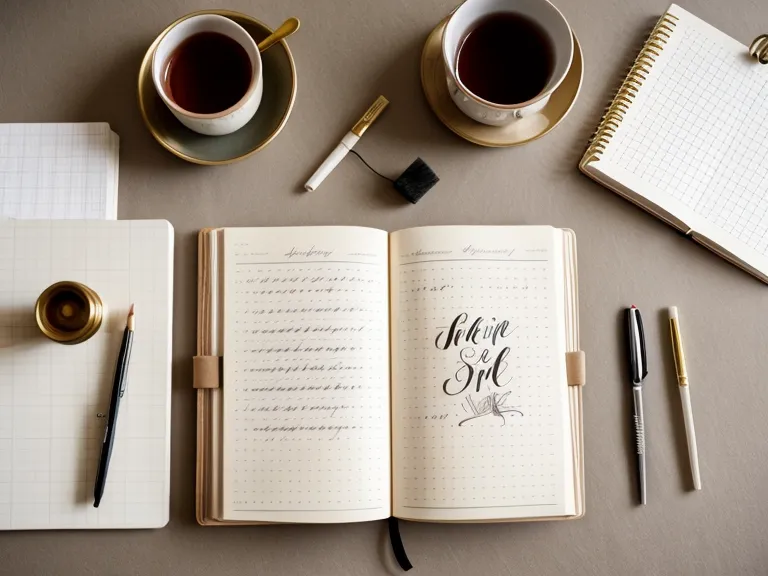
Achtzehn Übungsbögen liegen in der Mappe, mit der ich meinen Lernfortschritt tracke, jede Seite oben mit dem Namen des Kurses beschriftet, aus dem sie stammt. Diese Sammlung beantwortet die Frage nach der Handlettering lernen Dauer ehrlicher als jeder Vorher-Nachher-Post im Netz: Wer wissen will, wie lange es bis zu einem sauberen Schriftbild dauert, sollte weniger auf Kalenderwochen schauen und mehr auf die reine Anzahl der Übungseinheiten. Bei drei bis fünf Einheiten pro Woche zeigt sich ein spürbar saubereres Schriftbild nach sechs bis zwölf Wochen – wechselt man dabei die Technik, etwa von Monoline zu Brush, beginnt diese Uhr wieder bei null. Genau diesen Unterschied zwischen einem strukturierten Handlettering-Kurs und freiem Üben ohne Plan lege ich hier nebeneinander, mitsamt den Brushlettering-Tipps, die in keinem der beiden Wege von selbst auftauchen.
Zehn Stunden zielgerichtetes Kursüben brachten in meiner Auswertung mehr als hundert Tage plansloses Kritzeln vor dem Fernseher – ein Verhältnis, das die meisten Anfängerinnen unterschätzen, wenn sie sich für einen der beiden Wege entscheiden müssen. Unstrukturiertes Üben wiederholt vor allem die eigenen Fehler, weil niemand die Handhaltung korrigiert oder den Neigungswinkel des Brush Pens infrage stellt. Ein Kurs mit Progression zwingt genau dazu: langsamer schreiben, bewusster hinschauen, den nächsten Strich erst beginnen, wenn der vorherige sitzt.
Strukturierte Handlettering-Kurse für schnelleren Fortschritt
Zwei Ausgangslagen, gleiches Ziel: Fall eins ist eine Anfängerin, die sich einen Kurs mit klarer Reihenfolge sucht und wöchentlich feste Zeiten blockt. Fall zwei ist jemand, die sich Videos nach Lust und Laune ansieht und zwischendurch übt, wenn die Stimmung passt. Nach den gleichen zwanzig Stunden reiner Übungszeit sitzt bei Fall eins der Aufstrich schon spürbar ruhiger, während Fall zwei oft noch an der Frage hängt, welchen Winkel der Stift überhaupt haben soll. Der Unterschied liegt selten am Talent und fast immer an der Struktur: Ein Kurs baut Übungen so, dass jede neue Lektion auf der Motorik der vorherigen aufsitzt, während freies Üben denselben Fehler zehnmal wiederholen kann, ohne dass es auffällt.
Normales Druckerpapier zieht die Filzspitze regelrecht auseinander: Der Stift hakt bei jedem Abstrich, statt zu gleiten, weil die Fasern nicht standhalten – eine Erfahrung, die ich selbst gemacht habe und die jeden weiteren Fortschritt ausbremst, solange sie nicht korrigiert wird. Welches Papier zu welchem Stift wirklich passt, ist ein eigenes Kapitel für sich und würde hier zu weit führen. Wichtig ist nur: Wer an der Papierfrage scheitert, verwechselt oft ein Materialproblem mit einem Könnenproblem.
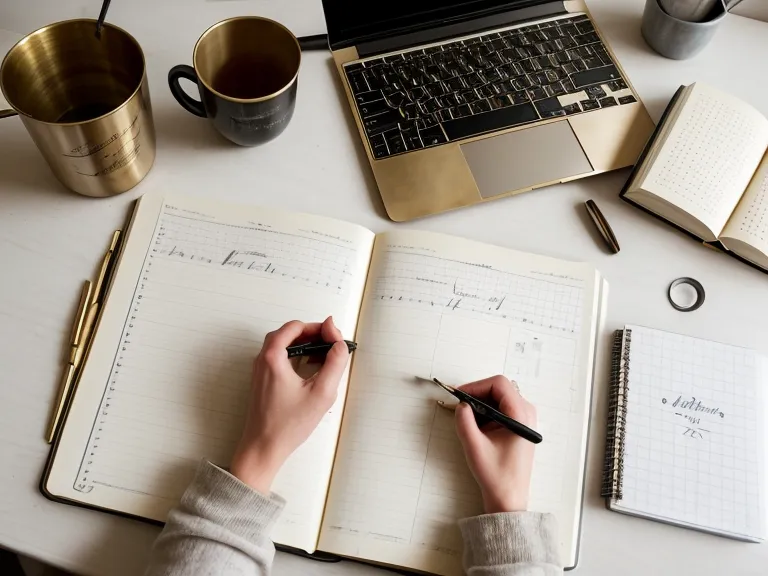
Übungsvolumen statt Kalenderzeit
Die Zahl, die in meiner Tracking-Tabelle mit Abstand am meisten aussagt, ist nicht das Datum, sondern die Summe der Übungsstunden. Bei drei bis fünf Einheiten pro Woche zeigt sich ein erkennbar saubereres Schriftbild nach sechs bis zwölf Wochen – das gilt für Monoline genauso wie für Brush, nur eben nicht gleichzeitig: Wer mitten in der Brush-Phase auf Monoline zurückwechselt oder umgekehrt, verschiebt diesen Zeitraum wieder nach hinten, weil die Hand ein neues Bewegungsmuster lernen muss. Begriffe wie Ober- und Unterlänge oder Serife sind dabei eher Vokabular als Fortschritt – sie beschreiben, was am Ende auf dem Papier steht, ändern aber nichts daran, wie viele Stunden bis dahin nötig waren. Wer noch keinen Brush Pen besitzt, kann diesen Rhythmus sogar mit einem gewöhnlichen Fineliner über Faux Calligraphy nachvollziehen, auch wenn das technisch ein anderes Thema ist.
Diesen Umschlagpunkt erkennt man meist an einem einzigen Wort, nicht an einer Lektion. Bei mir war es das Wort „Frühling": Ich schrieb es hin und sah zum ersten Mal, dass alle vier Grundstriche gleich breit nebeneinanderstanden – die Hand hatte die Regel übernommen, statt sie bei jedem Buchstaben neu zu berechnen. Die Feder kratzte dabei kaum hörbar über das körnige Papier, fast so, als würde sie selbst wissen, wo der Druck ansetzen muss.
Die Grundstriche entscheiden, bevor das erste Wort entsteht
Acht klassische Grundstriche bilden das Fundament, auf dem jedes spätere Wort steht: der dünne Aufstrich, der dicke Abstrich, der Umkehrschwung, das Oval und ihre Kombinationen mit Richtungswechsel. Für die reine Beherrschung dieser Striche sind grob 15 bis 20 Übungsstunden realistisch, was bei einem Teilzeit-Alltag mit Wochenendterminen einiges an Geduld verlangt, ohne dass in dieser Zeit ein einziges vollständiges Wort entsteht. Genau in dieser Phase franst auch die erste Brush-Pen-Spitze aus, meist schneller, als man denkt, wenn der Neigungswinkel nicht stimmt. Wie sich der Druck über die einzelnen Übungsschritte hinweg steigert, habe ich in meinem systematischen Handlettering Kursplan genauer aufgeschlüsselt.
Zwischen Kurs und freiem Üben entscheiden
Einen strukturierten Kurs wählen, wer ein verlässliches Zeitfenster will und keine Lust hat, die eigene Übungsreihenfolge aus zusammengesuchten Clips selbst zusammenzubauen: Die Progression von Grundstrich zu Wort zu Verbindung ist dann bereits durchdacht, und die sechs bis zwölf Wochen bis zum sauberen Schriftbild gelten unter der Voraussetzung, dass man der Reihenfolge treu bleibt. Freies Üben eignet sich eher für jemanden, der zuerst herausfinden will, ob Handlettering überhaupt das richtige Hobby ist, bevor Geld und feste Zeitblöcke investiert werden – dafür dauert der Weg zum gleichen Ergebnis erfahrungsgemäß deutlich länger und mit mehr Umwegen über falsche Stifte und ungeeignetes Papier. Wer schon einen Kurs abgeschlossen hat und nur die Anbieter vergleichen will, findet die Unterschiede in Aufbau und Tempo in meinem Handlettering Online Kurs Vergleich gegenübergestellt. Wie sich Kursstrukturen zwischen einzelnen Anbietern unterscheiden – Reihenfolge der Lektionen, Feedbackrunden, Umfang des Übungsmaterials – ist noch mal ein eigener Vergleich für sich, den ich hier nicht wiederhole.
Ein Nachbar von mir zieht seit einiger Zeit Gemüse in einem Hochbeet auf dem Balkon, und wenn er von der Geduld bis zur ersten Ernte erzählt, erkenne ich das gleiche Prinzip wie beim Lettering: Wiederholung schlägt Ungeduld, ganz gleich ob Samen oder Buchstaben. Digitales Lettering mit Stift und Tablet in Procreate folgt dabei einer eigenen Zeitrechnung, weil Ebenen und die Rückgängig-Taste Fehler anders verzeihen als Tinte auf Papier – das ist aber ein eigenes Kapitel, das ich an anderer Stelle ausführlicher behandle.
Was am Ende zählt: Wiederholung, nicht Talent
Wer heute fragt, wie lange Handlettering wirklich dauert, bekommt von mir eine nüchterne Antwort: Rechnen Sie mit 50 bis 70 Stunden konzentrierter Übung, um von den ersten wackeligen Strichen zu einem Schriftbild zu kommen, das man ohne Zögern verschenkt. Keine teureren Stifte und kein zusätzlicher Papierkauf verkürzen diese Zahl – nur die Qualität der Reihenfolge, in der geübt wird, tut das. Für alle, die diese Basis schon sicher beherrschen und als Nächstes an Schnörkeln arbeiten wollen, habe ich die Progression in einem separaten Test zum Handlettering Kurs für Fortgeschrittene festgehalten. Tintenverschmierte Finger gehören dabei so oder so dazu, egal für welchen der beiden Wege man sich entscheidet.